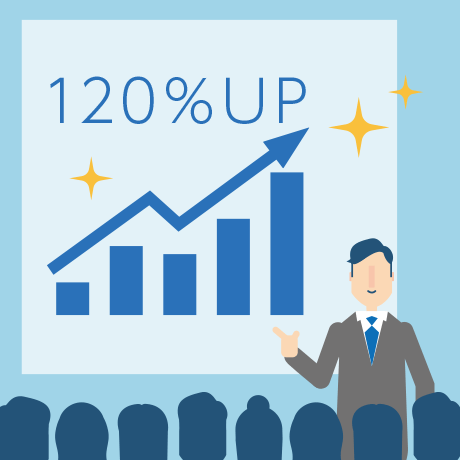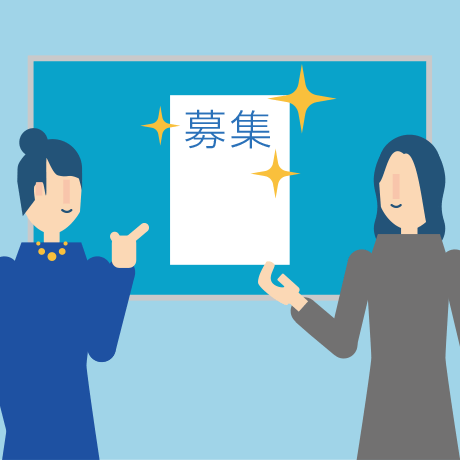
「自分は読めるから」
みんなも読めると
思っていませんか?
困っている人を助けるUDフォント、
それがMORISAWA BIZ+です。
「MORISAWA BIZ+」は大切なあなたの文書の内容が正しく伝わるよう、UDフォントの利用を提案する新しいサービス。
「文字のかたちがわかりやすいこと」「読みまちがえにくいこと」「文章が読みやすいこと」を
コンセプトに開発された「MORISAWA BIZ+」では、年齢や性別などにかかわらず、多くの人々が利用しやすいように
「ユニバーサルデザイン(UD)」の思想を文字に込めています。
MORISAWA BIZ+収録フォントの特徴
文字のかたちがわかりやすい
文字サイズが小さくても読みやすい
読みまちがえにくい
Office アプリケーションに最適化
MORISAWA BIZ+は
こんなシーンでお使いいただけます
プレゼン発表
掲示物
説明資料
/窓口用書類
企画書
/お知らせ
全55書体MORISAWA BIZ+
多様なラインナップで「必ず伝えたい情報」「注意を促したい文言」「さりげなく添えたい文章」など、必要な表現に合わせてフォントを変えることが可能となり、情報の「伝わりやすさ」に大きな差がつきます。
全3書体MORISAWA BIZ+ 無償版
使えるUDフォントはBIZ UDゴシック/明朝の全3書体、まずはお気軽にお試しください。